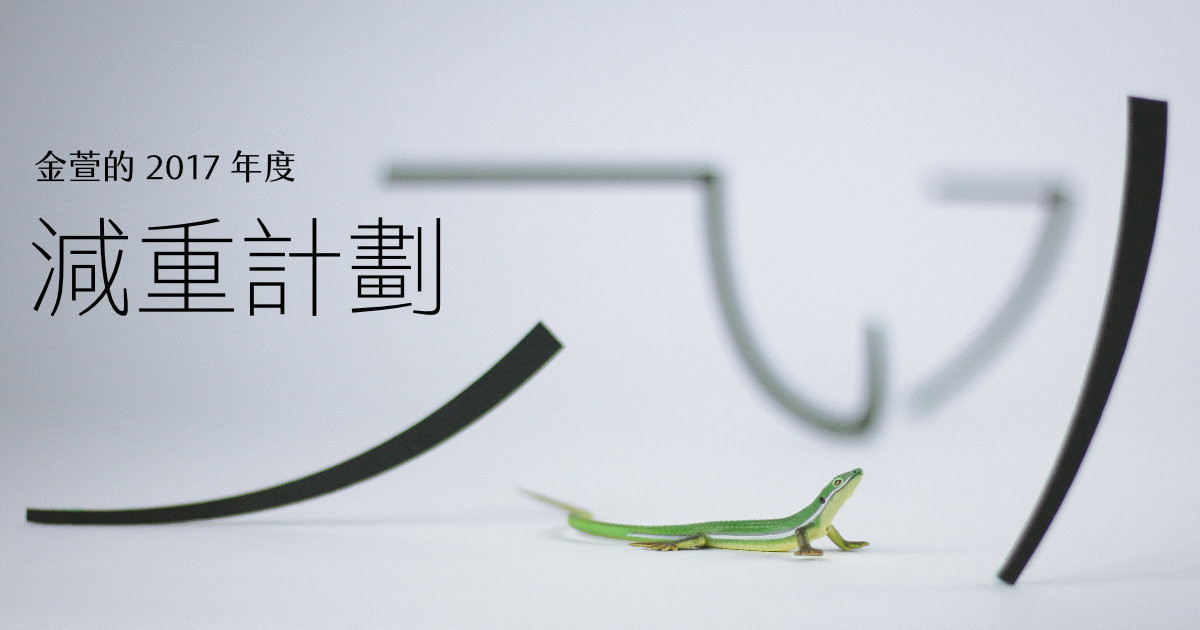
金萱字型家族即將於今年十月底迎接新成員:金萱微糖。
從二分糖 (W2) 到四分糖 (W4) 的粗細合稱為金萱微糖。包含會釋出給贊助者的金萱三分糖 (W3),都是適合用在內文排印的字型。
這種字型比起標題字(例如半糖以上),在設計時需要特別小心,以確保閱讀的流暢舒適,因此被視為是相當難以設計的字型。究竟設計金萱微糖是什麼樣的體驗,內文字型難做的地方在哪呢?
預計討論的問題有:
a. 運用金萱微糖的時候,要怎麼發揮它的長處?
b. 內文字型要怎麼設計?講細一點的話,筆畫粗細、框架、字面率要如何決定?
c. 半糖如何變成微糖?是重新描繪比較快?還是用軟體減細再調整
d. 對設計師來說,設計標題字與內文字的重點分別在於哪邊?